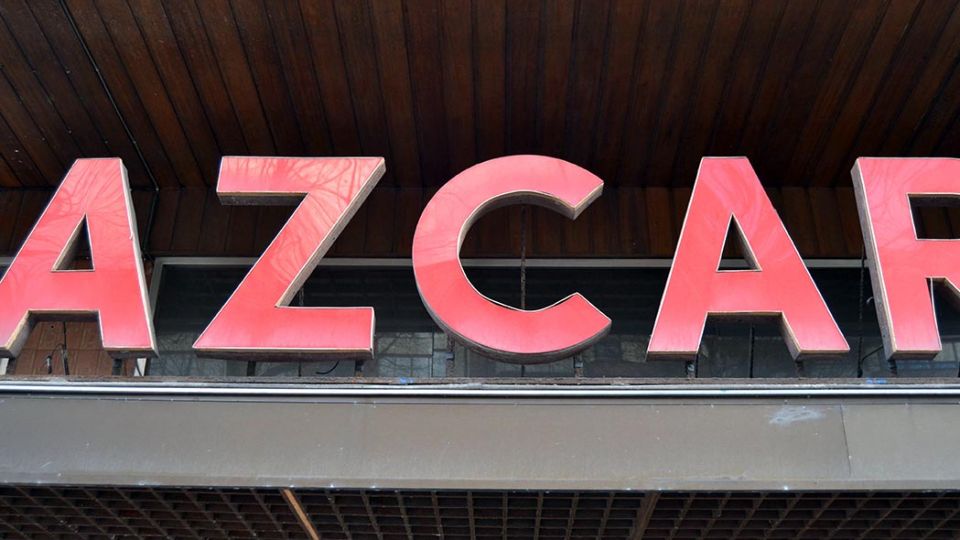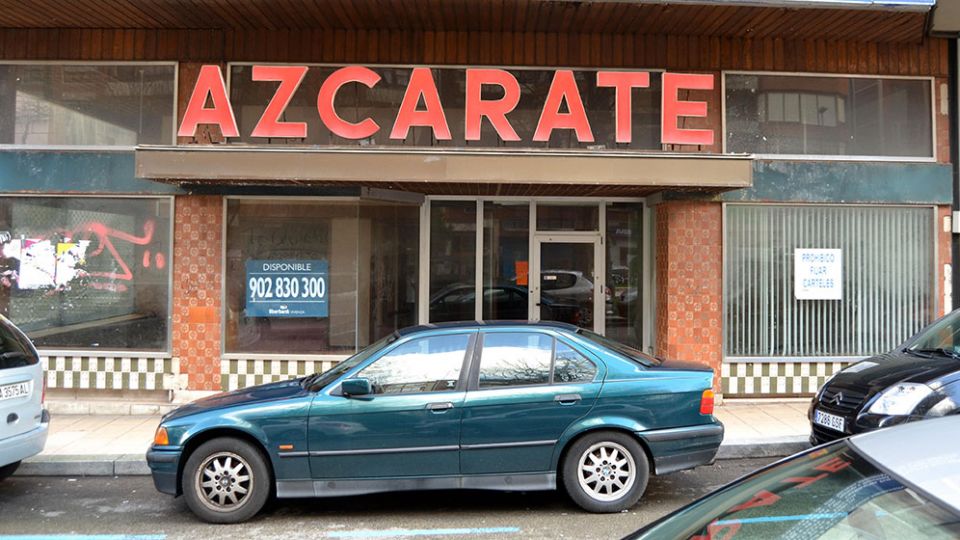
Almacenes Azcarate
Datación
1981
Estado
Desaparecido
Tipografía
Sans
Técnica
PCV
Localización
Enorme rótulo en tipo grande y capital y quizás uno de los más espectaculares. No hay mucha información al respecto de estos almacenes, vinculados al diseño de interiores y Muebles.